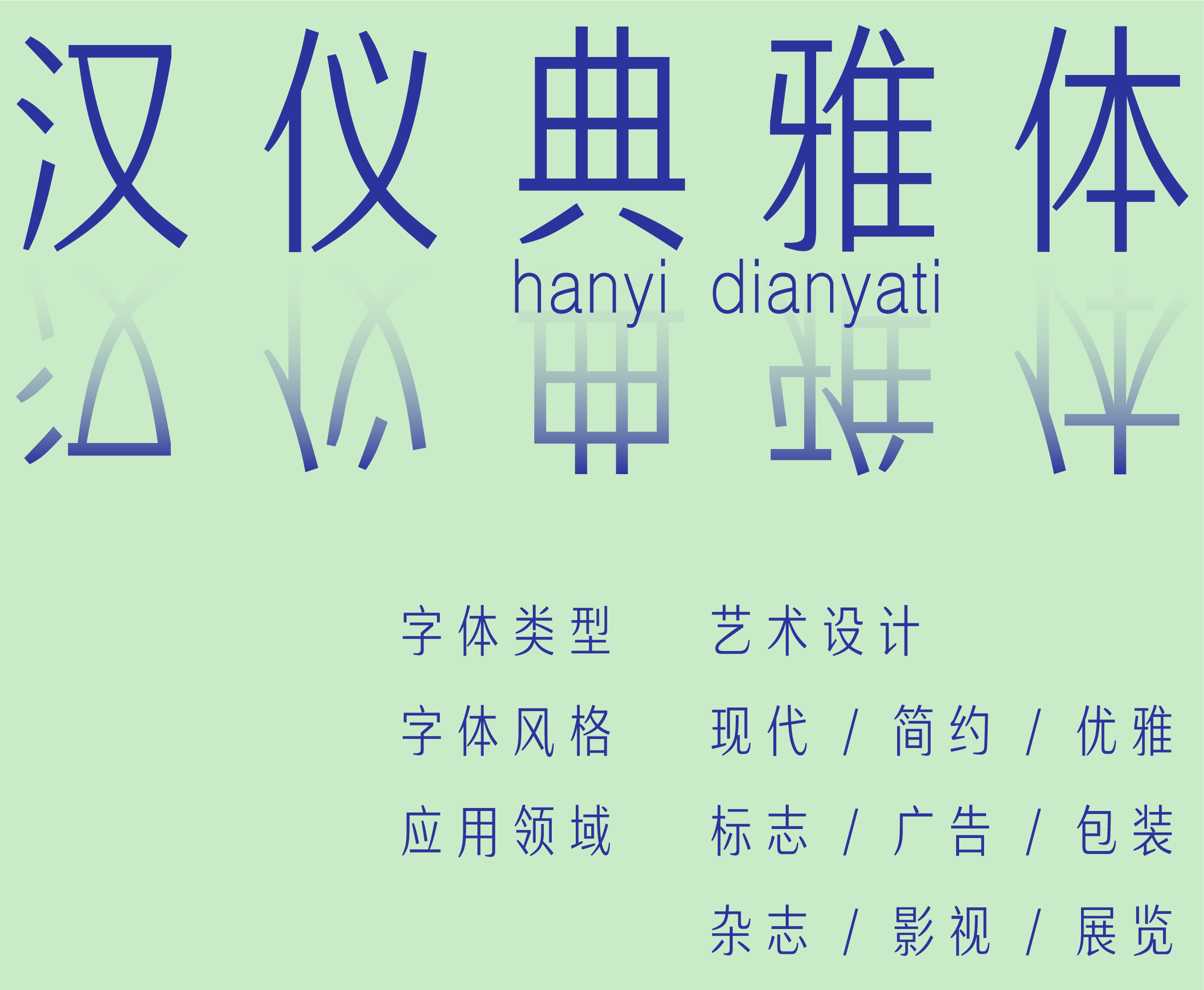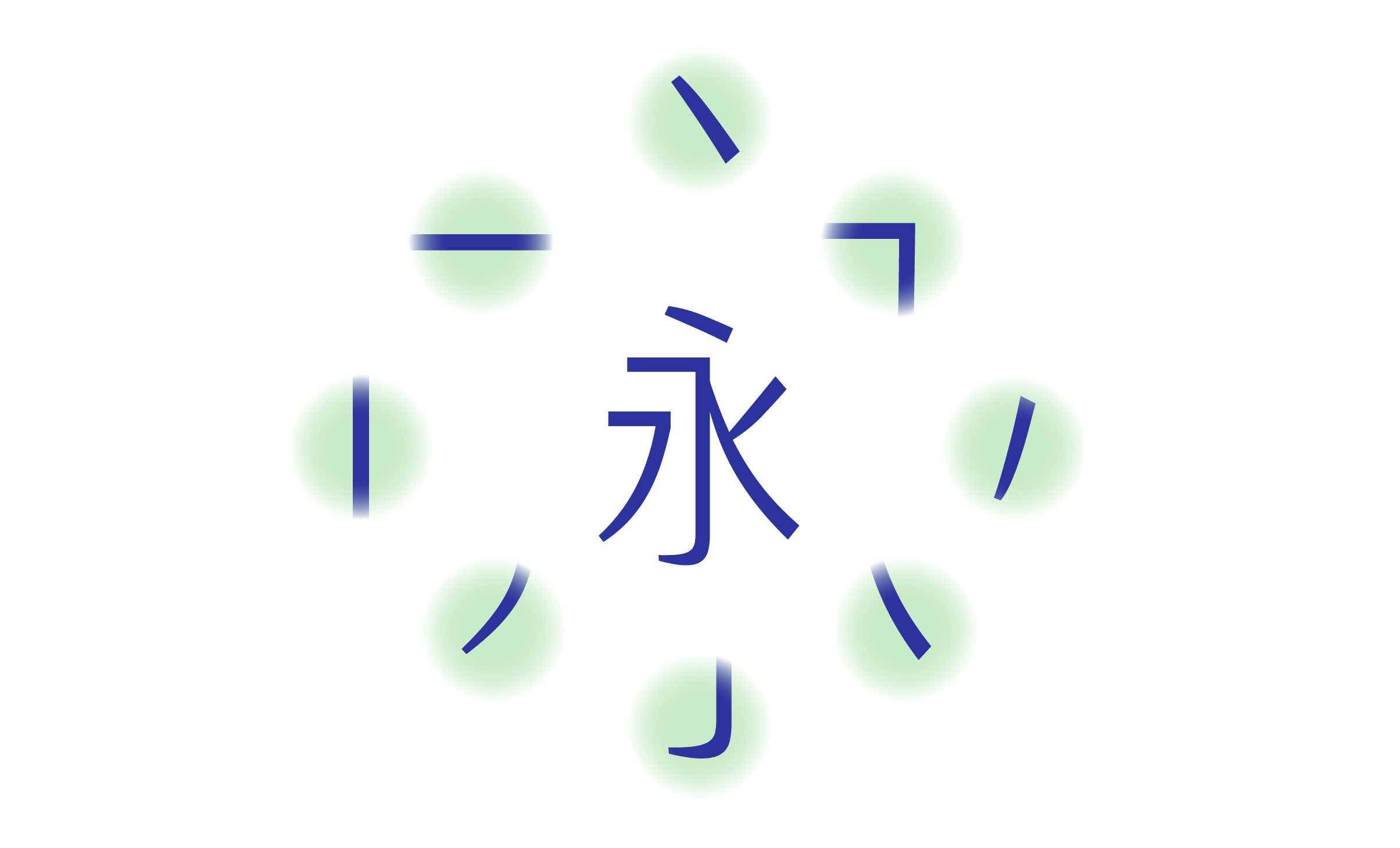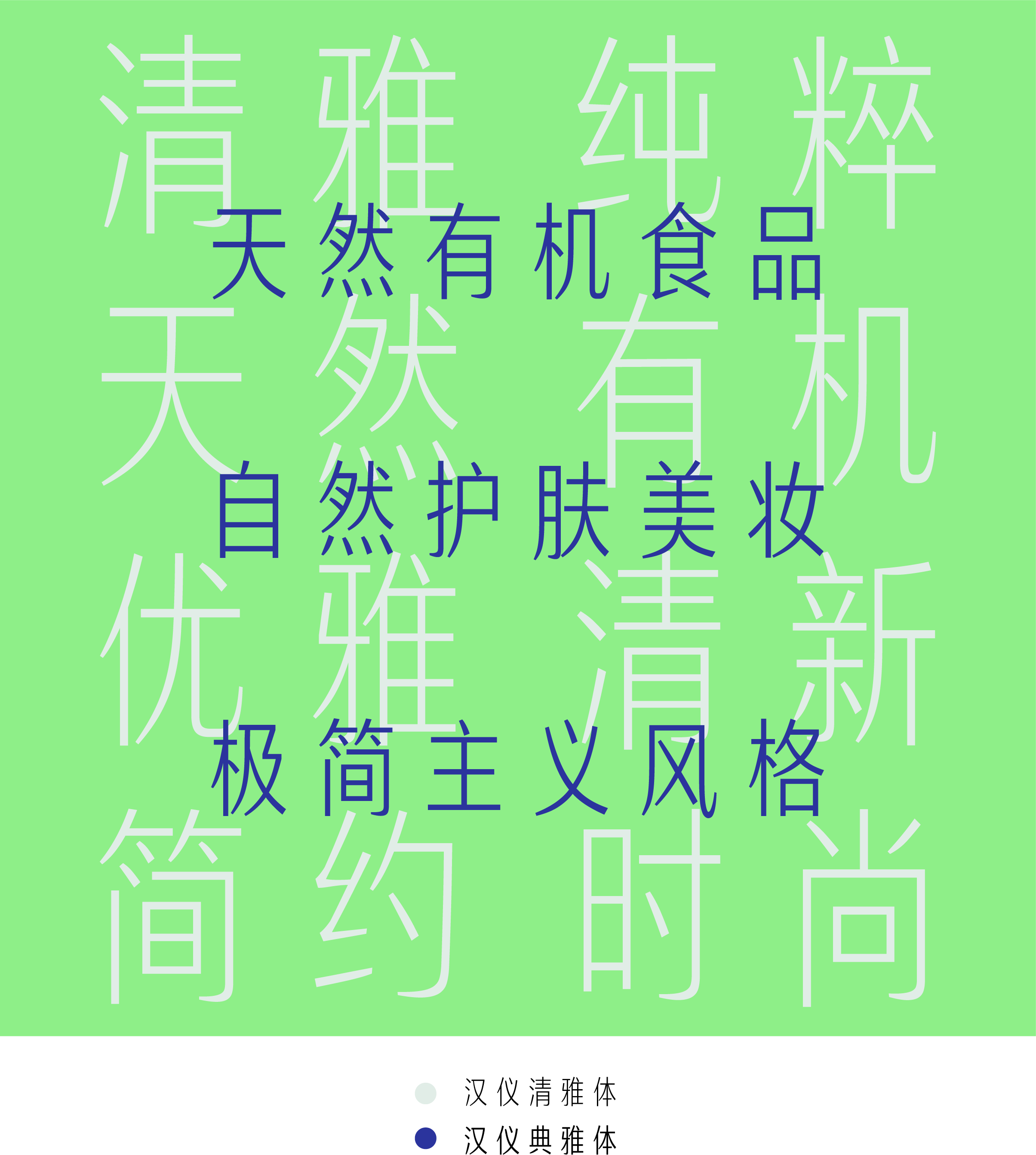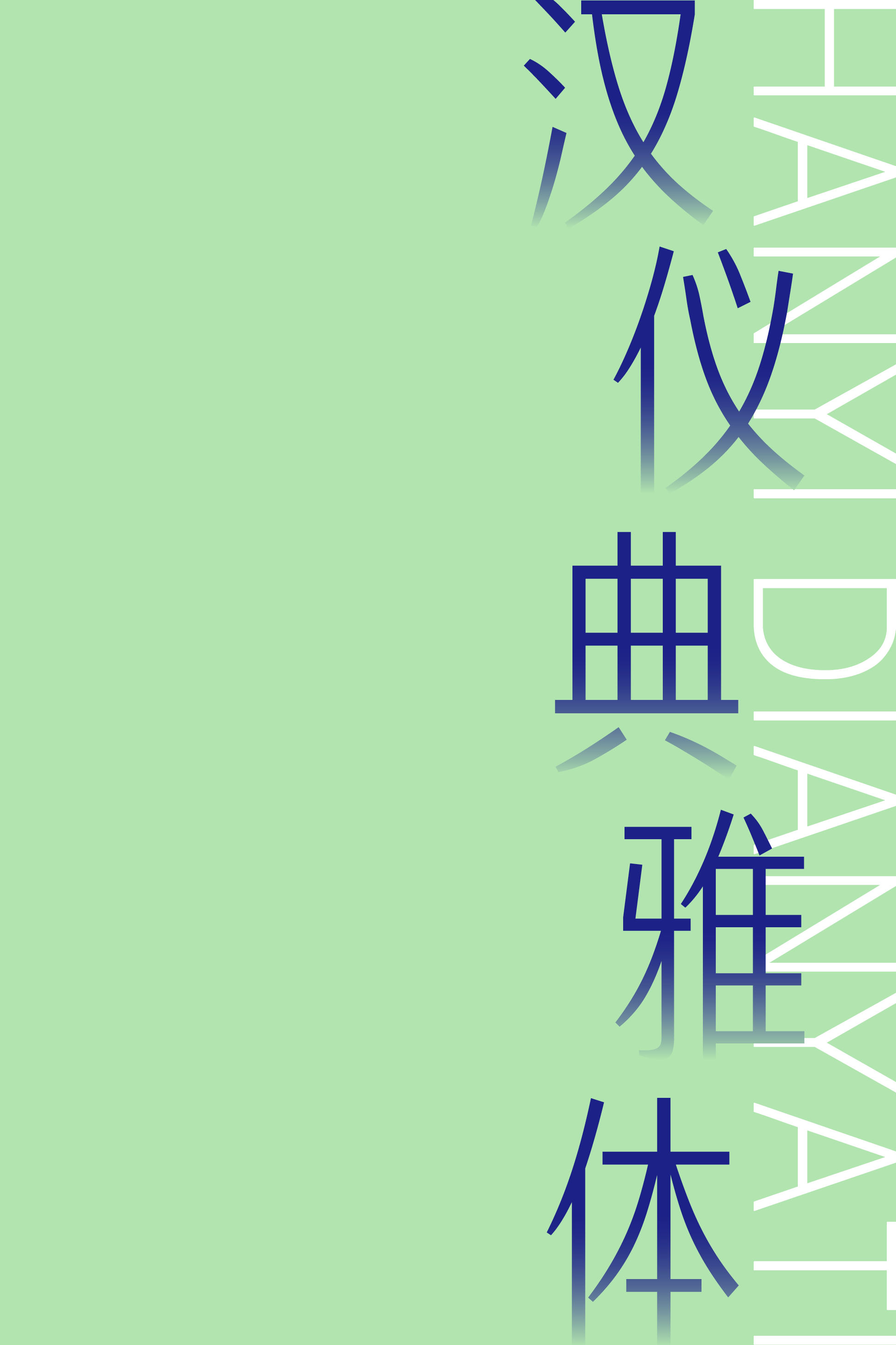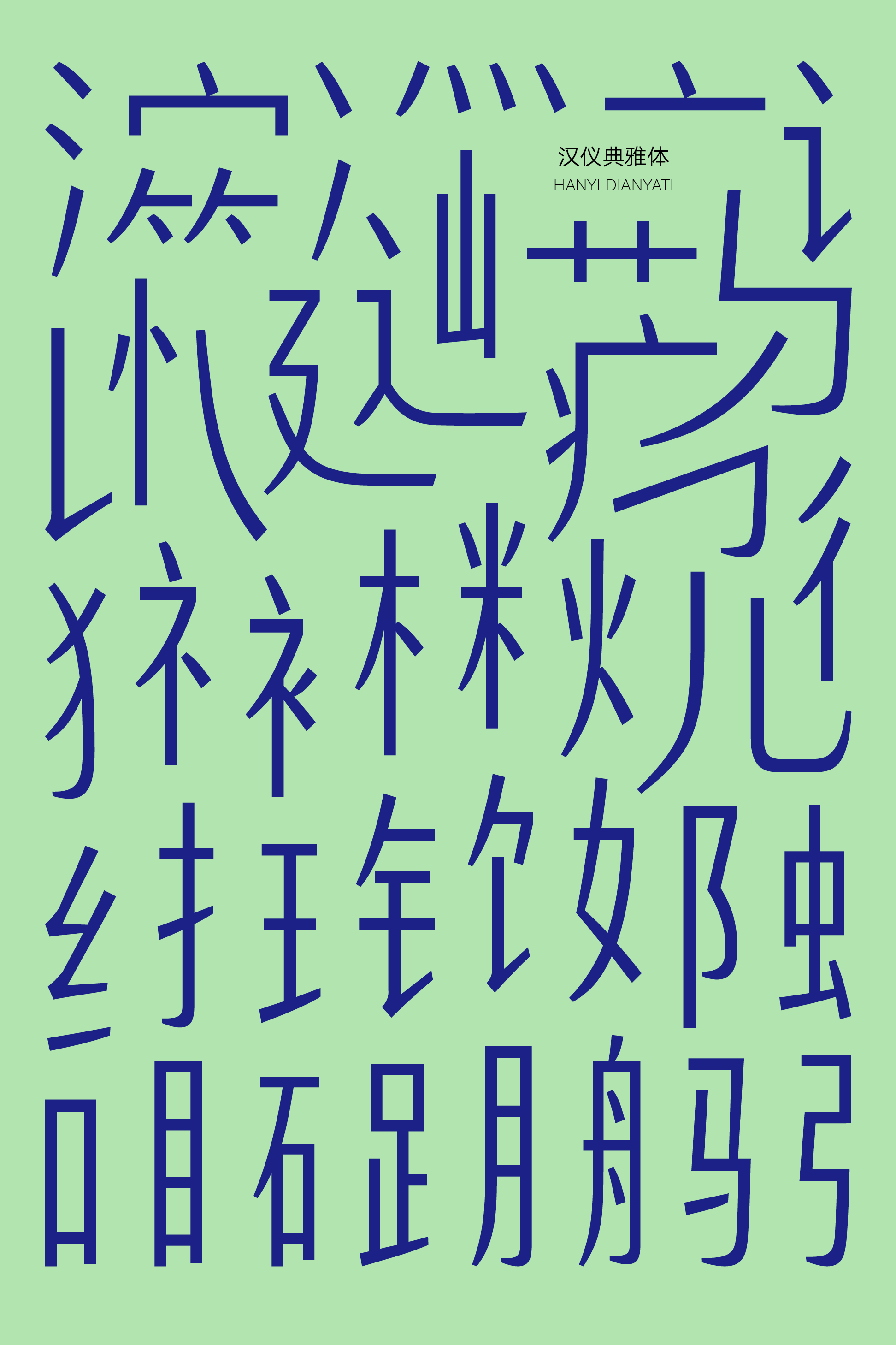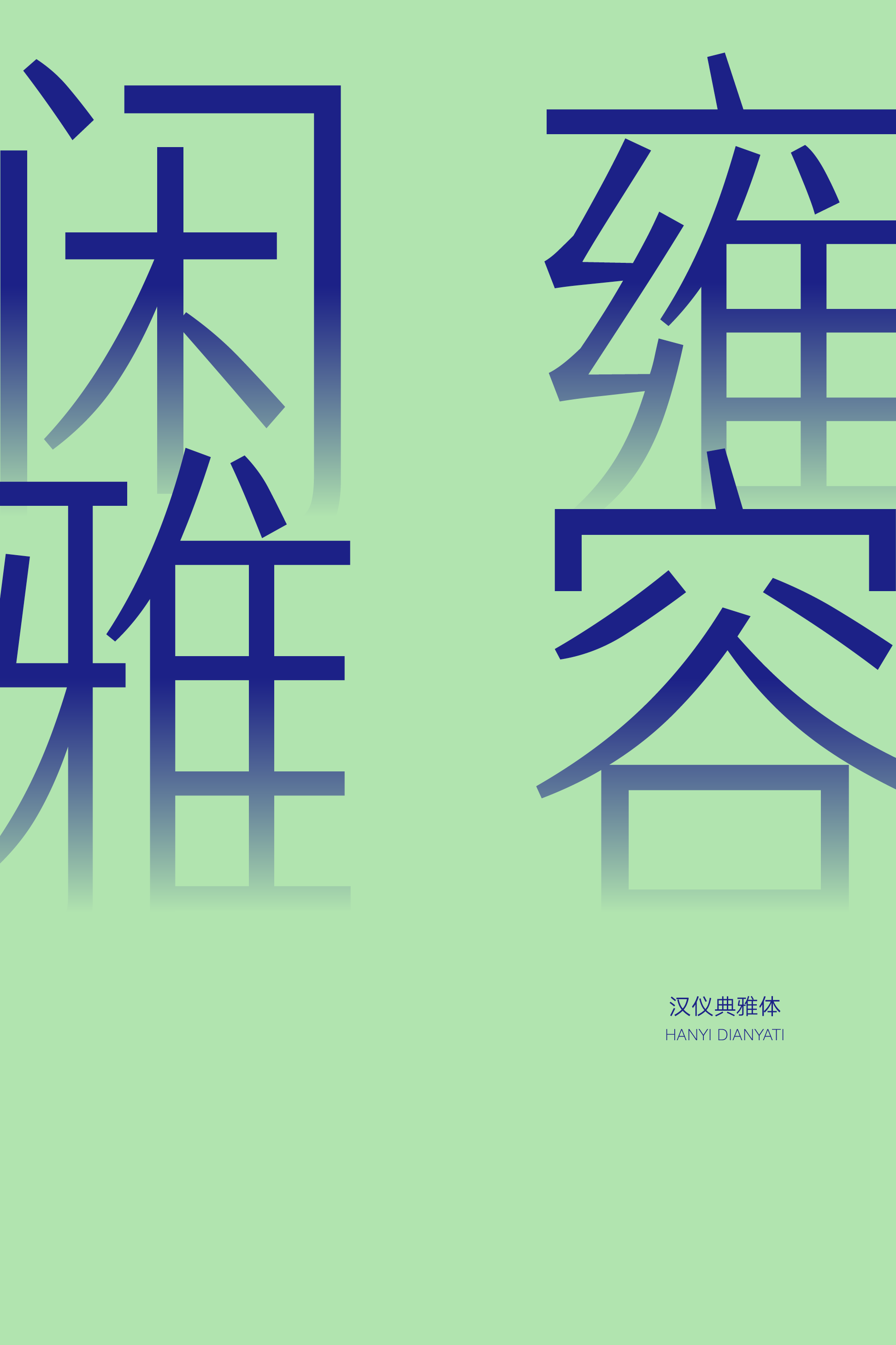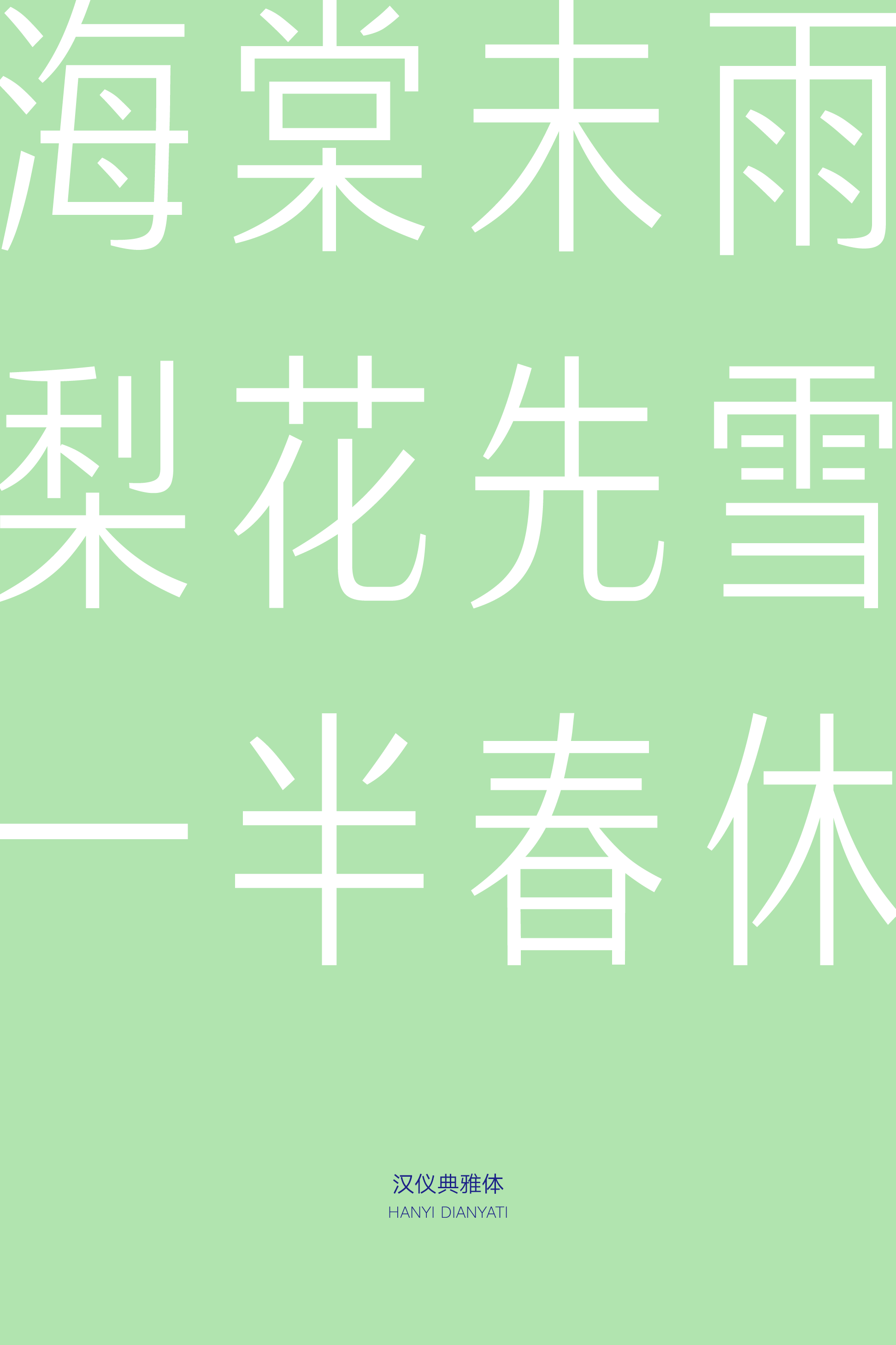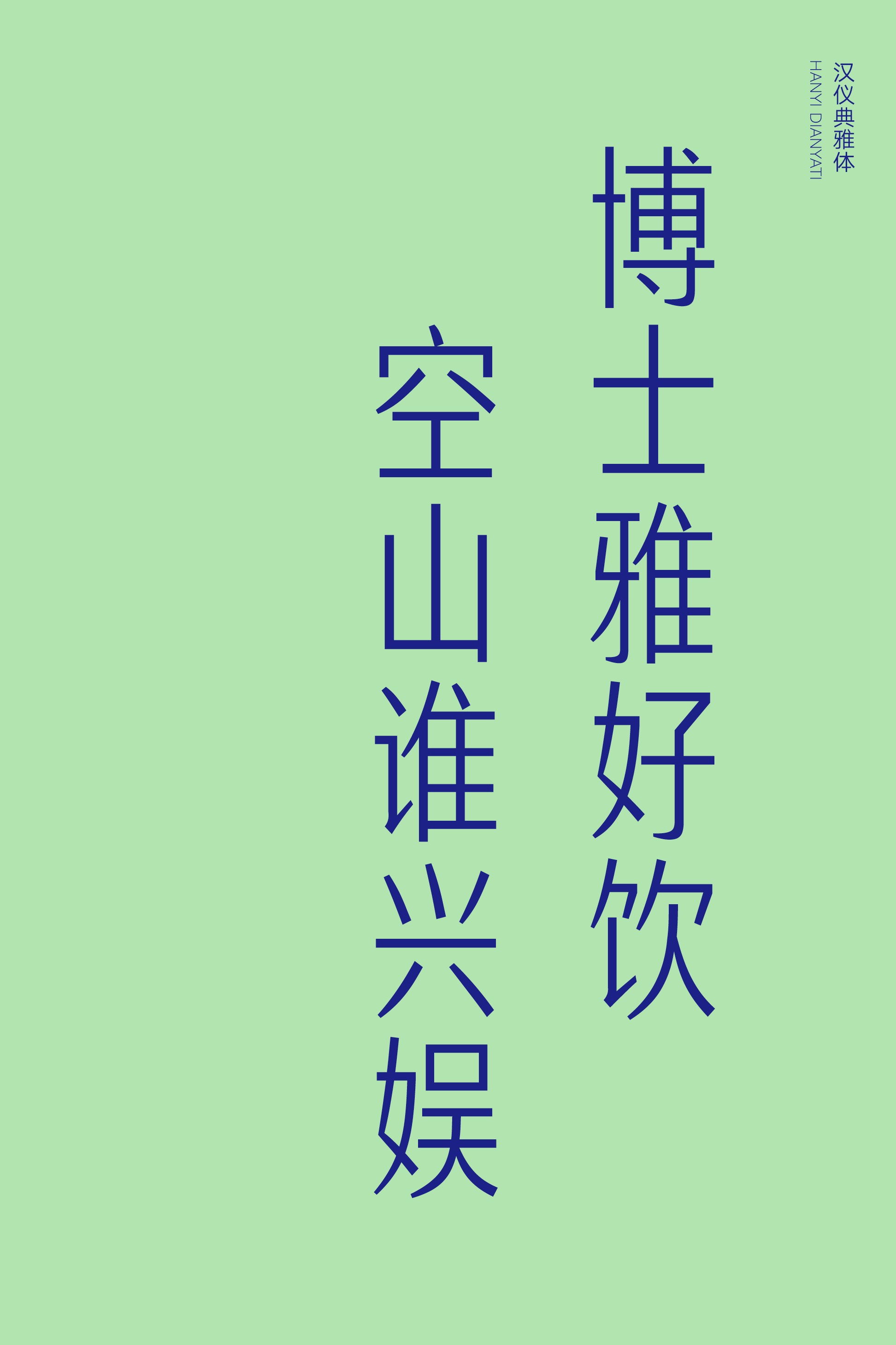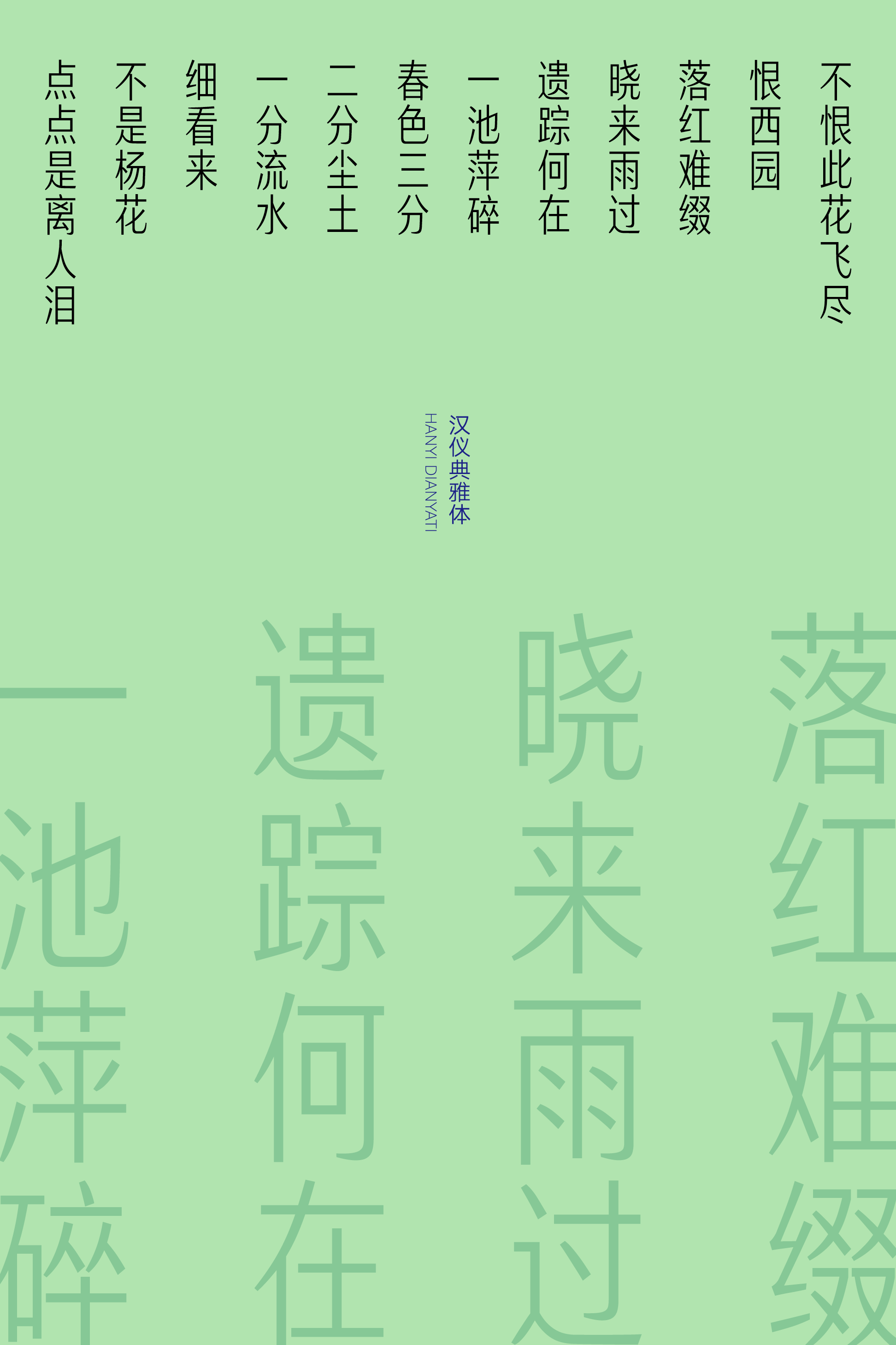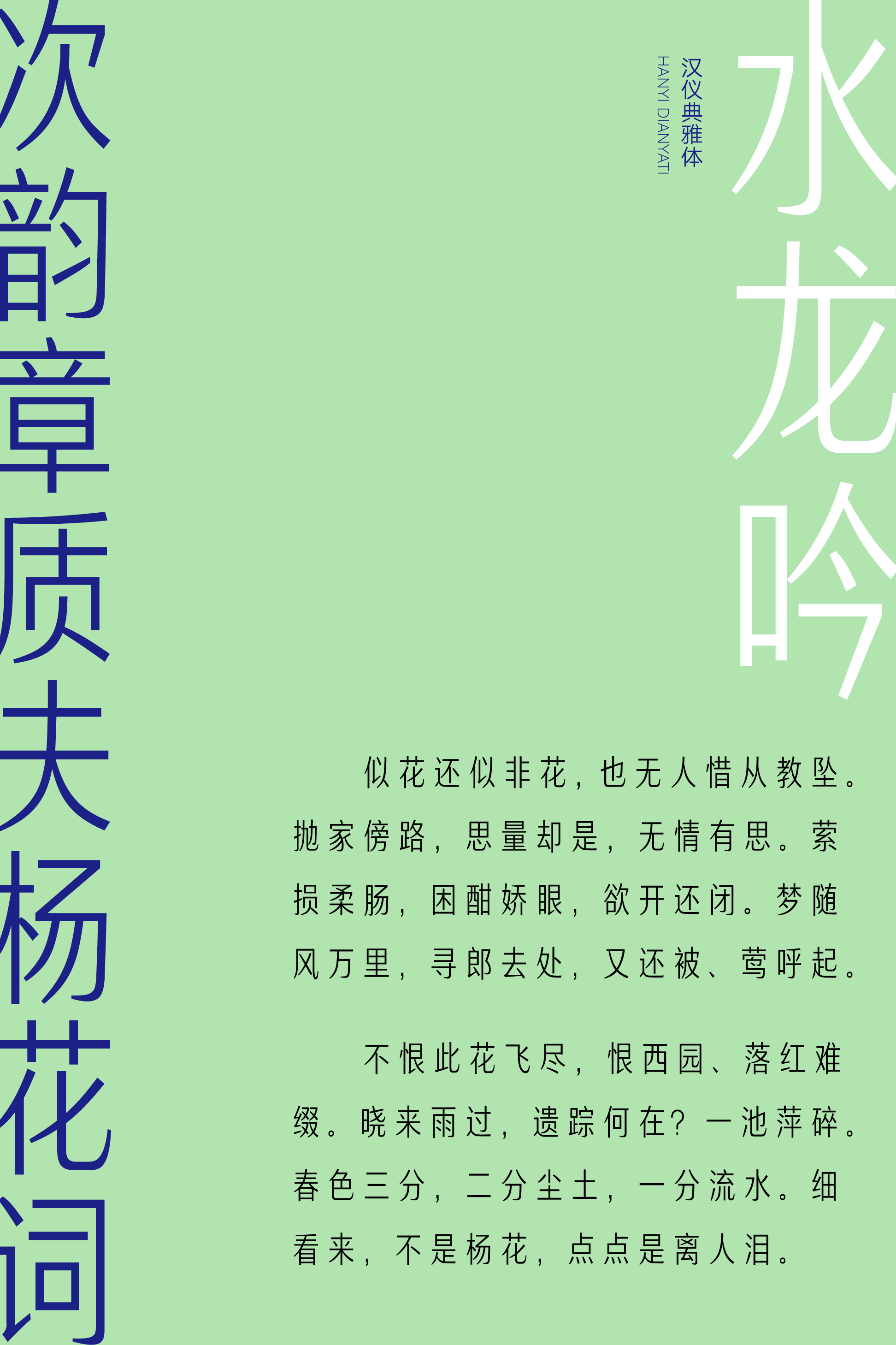
汉仪典雅体
汉仪典雅体,与汉仪清雅体为一组家族字体,有着同样高挑的字形和柔韧的笔画,线条稍有加粗,为优雅的气质增添了一分沉稳。汉仪典雅体,端庄大方,温柔沉静,可与纤细的汉仪清雅体搭配使用,应用于天然有机、清新优雅、简约时尚的品牌,字里行间尽显优雅气质。
字形高挑,端正挺拔。
笔画简约,柔韧稳重。
可与线条纤细的汉仪清雅体搭配使用,适合天然有机、清新优雅、简约时尚的使用场景。